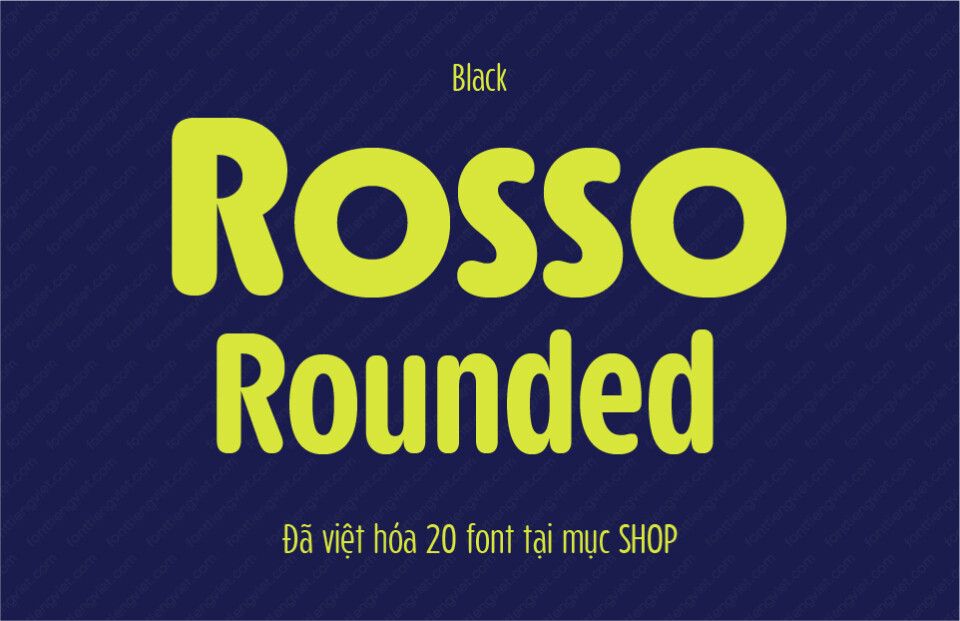
Font Việt hóa 1FTV VIP Rosso Rounded Black
Tải Font Việt hóa 1FTV VIP Rosso Rounded Black Miễn Phí Cho Thiết Kế Ấn Tượng
Trong thế giới đồ họa hiện đại, việc lựa chọn một bộ Font Miễn Phí chất lượng luôn là ưu tiên hàng đầu của các nhà thiết kế và học sinh sinh viên. Một trong những cái tên đang gây chú ý mạnh mẽ trong cộng đồng sáng tạo chính là Font Việt hóa 1FTV VIP Rosso Rounded Black. Đây là một phông chữ mang phong cách hiện đại, nổi bật với những đường nét bo tròn mềm mại nhưng vẫn giữ được sự mạnh mẽ, đậm nét (Black). Bài viết này sẽ giúp bạn hiểu rõ tại sao bộ font này lại trở thành lựa chọn hoàn hảo cho các dự án thiết kế học đường và truyền thông tại Việt Nam hiện nay.
Đặc điểm nổi bật của Font Việt hóa 1FTV VIP Rosso Rounded Black
Bộ Font Việt hóa 1FTV VIP Rosso Rounded Black được thiết kế với độ dày cực lớn, tạo nên sự nhận diện thị giác rất cao ngay từ cái nhìn đầu tiên. Khác với những phông chữ góc cạnh cứng nhắc, Rosso Rounded sở hữu các góc bo tròn tinh tế, mang lại cảm giác thân thiện, gần gũi và đầy tính nghệ thuật. Điều này đặc biệt phù hợp khi bạn muốn truyền tải những thông điệp vui tươi, năng động nhưng không kém phần chuyên nghiệp. Bản Việt hóa giúp người dùng sử dụng đầy đủ các ký tự tiếng Việt có dấu mà không lo bị lỗi hiển thị, một điểm cộng cực lớn cho người dùng trong nước.
Tính ứng dụng linh hoạt trong giáo dục và thiết kế
Với phong cách độc đáo, Font Việt hóa 1FTV VIP Rosso Rounded Black cực kỳ thích hợp để làm tiêu đề cho các slide thuyết trình, poster sự kiện trường học hoặc bìa sách giáo khoa sáng tạo. Nhờ đặc tính “Black” (siêu đậm), phông chữ này giúp các từ khóa quan trọng trở nên nổi bật trên nền hình ảnh phức tạp. Các bạn học sinh có thể dùng nó để trang trí báo tường điện tử hoặc làm nội dung video trên mạng xã hội, tạo nên một dấu ấn cá nhân rõ nét. Ngoài ra, tính năng bo tròn của font cũng giúp giảm bớt sự căng thẳng, tạo không khí học tập thoải mái và tràn đầy cảm hứng.
Lợi ích khi sử dụng Font Việt hóa 1FTV VIP Rosso Rounded Black
Việc sử dụng Font Việt hóa 1FTV VIP Rosso Rounded Black không chỉ dừng lại ở yếu tố thẩm mỹ mà còn giúp tối ưu hóa quy trình làm việc. Bạn sẽ không phải tốn thời gian chỉnh sửa khoảng cách thủ công (kerning) vì bộ font đã được tinh chỉnh vô cùng chuyên nghiệp. Đặc biệt, cấu trúc chữ rõ ràng giúp người đọc dễ dàng tiếp nhận thông tin ngay cả khi quan sát từ khoảng cách xa. Đây là yếu tố then chốt giúp các sản phẩm thiết kế của bạn đạt được hiệu quả truyền thông cao nhất, đảm bảo tính thẩm mỹ đồng nhất trên mọi nền tảng từ in ấn đến hiển thị kỹ thuật số.
Cách kết hợp font chữ hiệu quả
Để phát huy tối đa vẻ đẹp của Font Việt hóa 1FTV VIP Rosso Rounded Black, bạn nên kết hợp nó với các phông chữ không chân (sans-serif) mảnh hơn cho phần nội dung chi tiết. Sự tương phản giữa nét đậm của Rosso và nét thanh của các font bổ trợ sẽ tạo nên một bố cục hài hòa, dễ nhìn. Đừng quên chú ý đến khoảng cách dòng và màu sắc để tạo nên những tác phẩm thiết kế mang tính giáo dục sâu sắc và hiện đại. Việc nắm vững cách phối hợp này sẽ giúp bạn nâng tầm kỹ năng trình bày văn bản một cách đáng kể.
Kết luận về bộ font chữ độc đáo